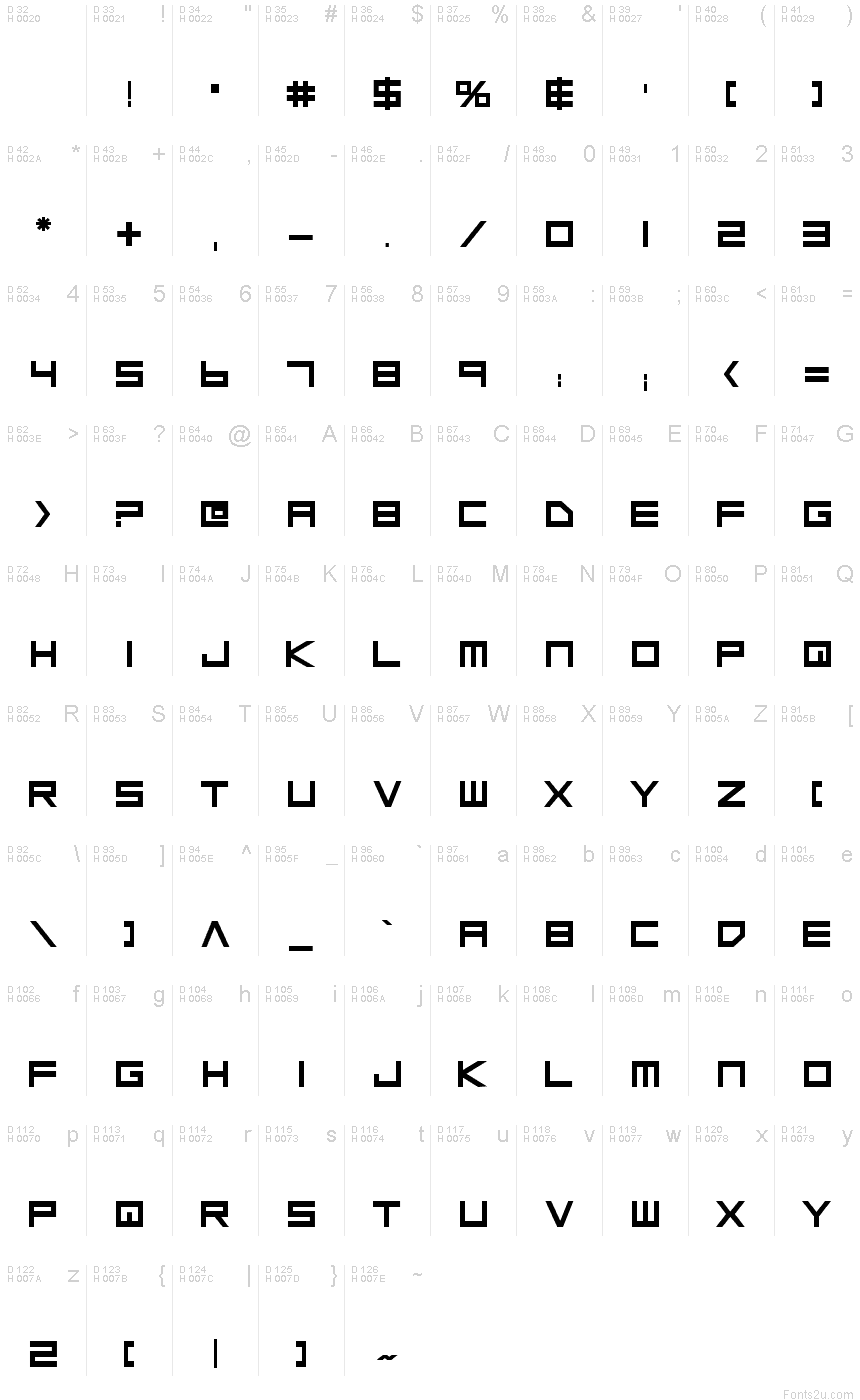
Low Gun Screen Bold, disegnato da Iconian Fonts nel 2007, è un carattere display geometrico in stile techno gratuito con una struttura rigorosa e modulare. Le sue maiuscole squadrate utilizzano angoli retti, tratti spessi e spazi interni ristretti che ricordano le scritte digitali segmentate.
Le interfacce di gioco e i poster di fantascienza possono sfruttare le sue forme rigide per evocare macchinari, pannelli di controllo e display a bassa risoluzione. La stessa costruzione si adatta al packaging di musica elettronica e al merchandising di e-sport, soprattutto quando si desidera un wordmark industriale compatto. Mantenete il layout circostante pulito in modo che le forme delle lettere squadrate rimangano facili da distinguere.
Low Gun Screen Bold